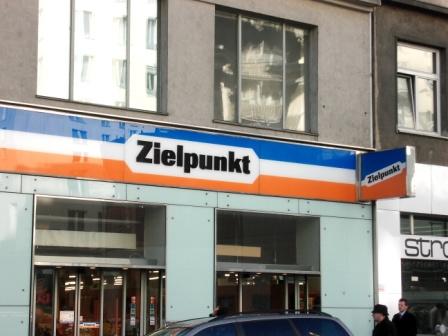
Plus-Supermarkt - welche Schrift?
ich bin auf der Suche nach einer Schriftart, die der des ehem. Discounters PLUS entspricht.
Gibbet nich. Das ist ein Logo, keine Schrift.
Ja, ich weiß ja, daß es ein Logo ist. :D
Aber es gibt ja von vielen anderen Logos auch Schriftarten.
Also könnte ich nur selber Buchstaben nachbilden und formen, ja?
Kann denn jemand die Schrift von Real identifizieren?
Oder die des österreichischen Zielpunkts?
Also könnte ich nur selber Buchstaben nachbilden und formen, ja?
ja. die schrift im plus-logo ist so speziell, dass nur mit geringer wahrscheinlichkeit mehr als genau diese vier buchstaben existieren. darum hat man wohl auch einen anderen font für das emblem der einstigen schwesterkette zielpunkt gewählt.
und ›Real‹ dürfte eine extrem garstig verzerrte futura sein:
So von nahem betrachtet, sieht das ja mal richtig beschissen aus.